웹툰에 쓸 폰트가 필요하다면? 한 컷 한 컷을 살려주는 효과음 폰트 4종
액션부터 감성까지, 장면을 움직이게 하는 폰트
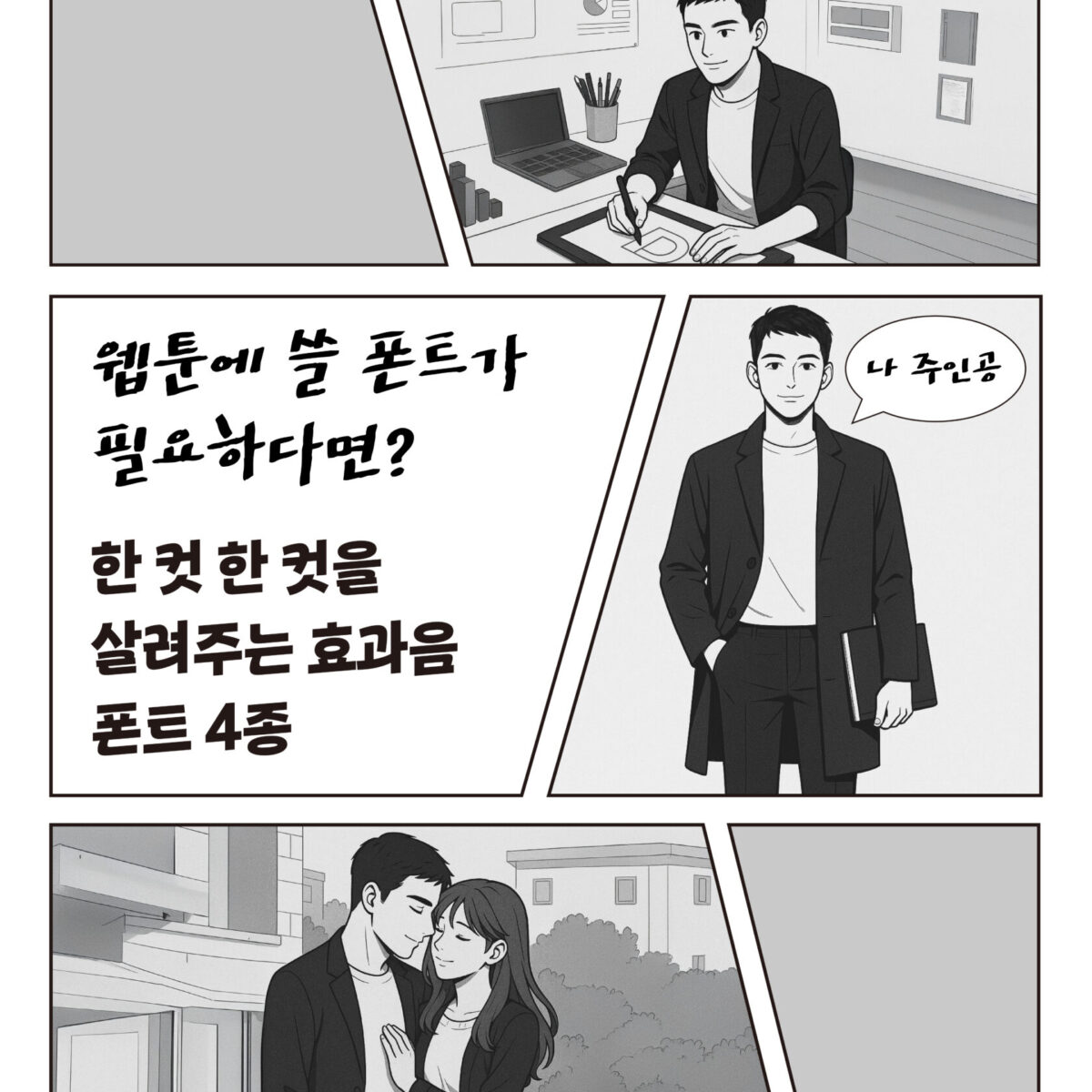
웹툰 한 컷마다 생동감을 살리는 포인트는? 바로 효과음이죠. “쿵” “털썩” “두근두근” — 이런 소리와 감정들이 제대로 느껴질 때, 컷의 힘이 더해지죠. 하지만 손글씨만으로는 표현에 한계가 있을 수 있습니다.
때문에 많은 분들이 웹툰의 완성도를 한층 높여주는 효과음 전용 폰트, 강렬한 액션부터 섬세한 감정선까지 장면에 딱 맞는 분위기를 연출해주는 폰트들을 찾고 있는데요. 효과음도, 감정도, 컷의 임팩트도 제대로 살려주는 산돌구름이 추천하는 폰트 4종을 소개합니다. 이 폰트들로 독자분들께 더 몰입감 있는 경험을 선사해보세요!
1. 기은(솔폰트)/Soul 그날오후
‘Soul 그날오후’는 드라마, 순정 로맨스 장르에서 다양하게 활용할 수 있는 폰트입니다. 중간 굵기의 매직펜을 눌러써 획의 시작과 끝이 동글동글하게 맺혀있는 손글씨의 맛을 살린 서체죠. 효과음 뿐만 아니라 말풍선 속 대화나 생각을 표현할 때도 어울리는 폰트로, 일상적이고 귀여운 필기체가 필요한 곳에 사용해 보세요!
2. 기은(솔폰트) /Soul 도원결의
‘Soul 무풍지대’는 액션, 무협, 시대극 등 거칠고 카리스마 있는 장르에 어울리는 효과음 폰트입니다. 매섭고 차가운 겨울바람이 연상되고, 갈필의 질감을 그대로 살려 장면 속 극적인 효과를 더욱 살려주죠. 효과음은 물론 웹툰의 표지나 타이틀용으로도 개성 있게 쓸 수 있는 폰트로 추천해요!
3. 준폰트/주간만화
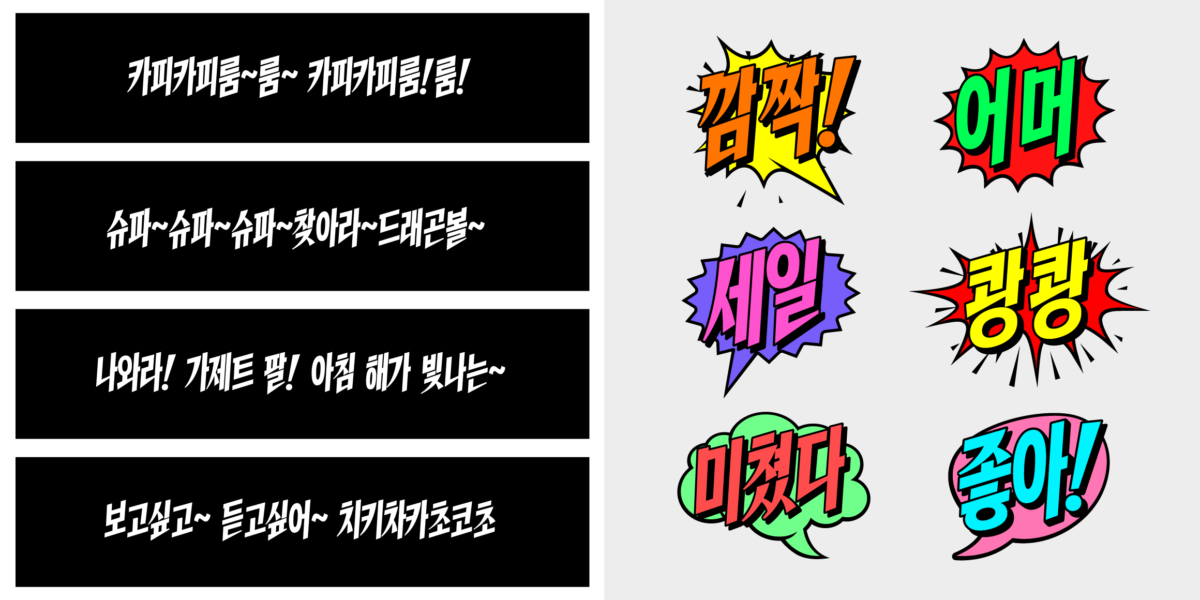
가벼운 액션물부터 코미디까지 어울릴 것 같은 이 폰트는 이름부터 ‘주간만화’입니다. 이름에 드러난 듯이 만화의 대사나 지문, 의성어, 의태어를 표현하기 위해 만들어진 폰트죠. 주목도가 높아 강조하기 위한 짧은 텍스트에 특히 잘 어울리기 때문에 예능 분위기의 영상 자막이나 썸네일에 활용하는 것도 추천 드립니다!
4. 윤디자인/Yoon 흑백영화
이번에 소개할 폰트도 특이한 효과를 적용한 폰트인데요. ‘Yoon 흑백영화’는 타자기의 아날로그한 감성을 표현한 폰트이지만, 어딘가 공포스러운 인상도 느껴지지 않나요? 오래되고 먼지 쌓인 타자기에서 사람 없이 글자가 타이핑 되는 모습을 한번 상상해보세요. 이렇게 원래 폰트에 효과만 적용해도 호러스러운 한 방울 첨가할 수 있죠. 불길한 내용의 대사 말풍선이나 효과음에 사용해 생동감을 더해보세요!